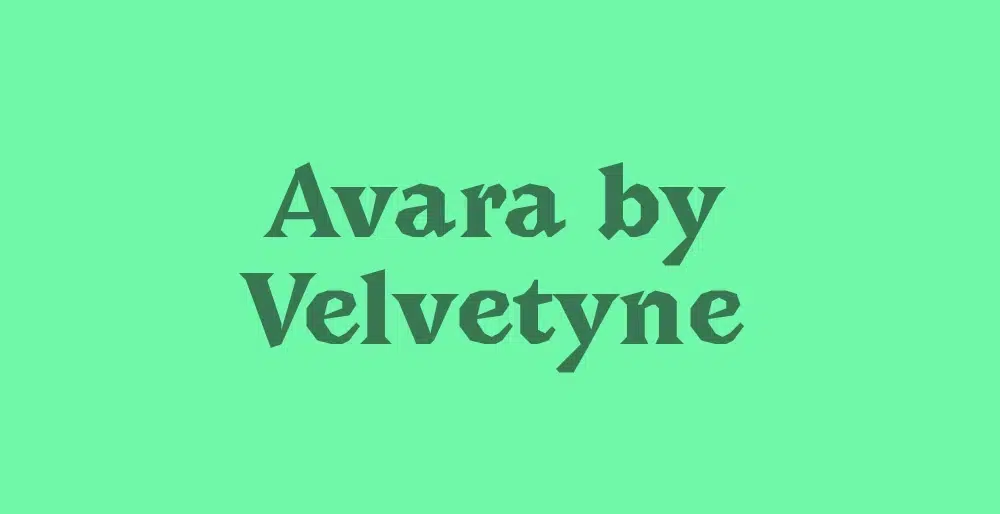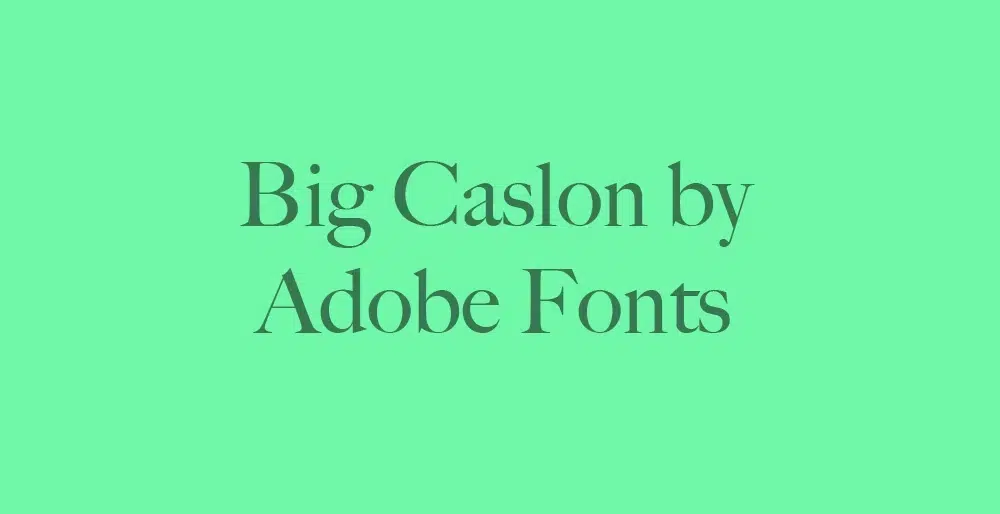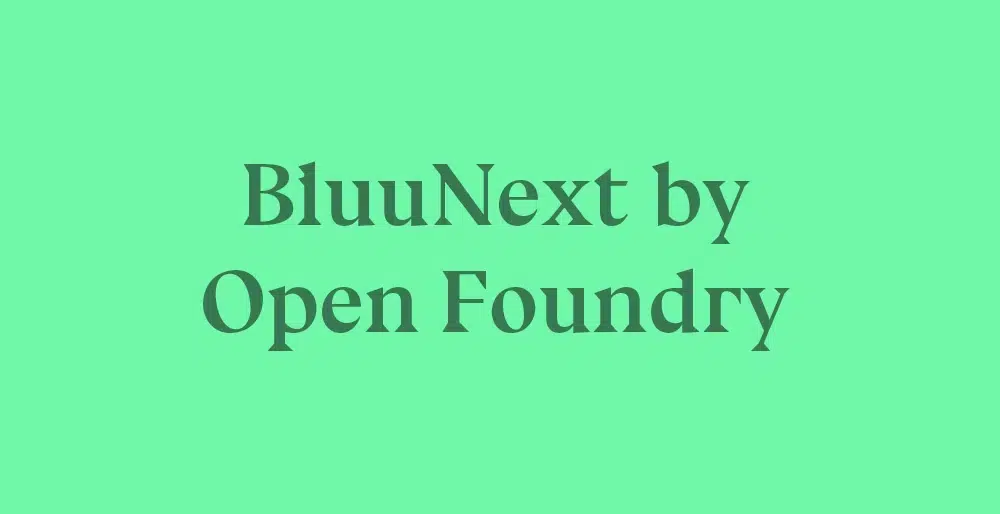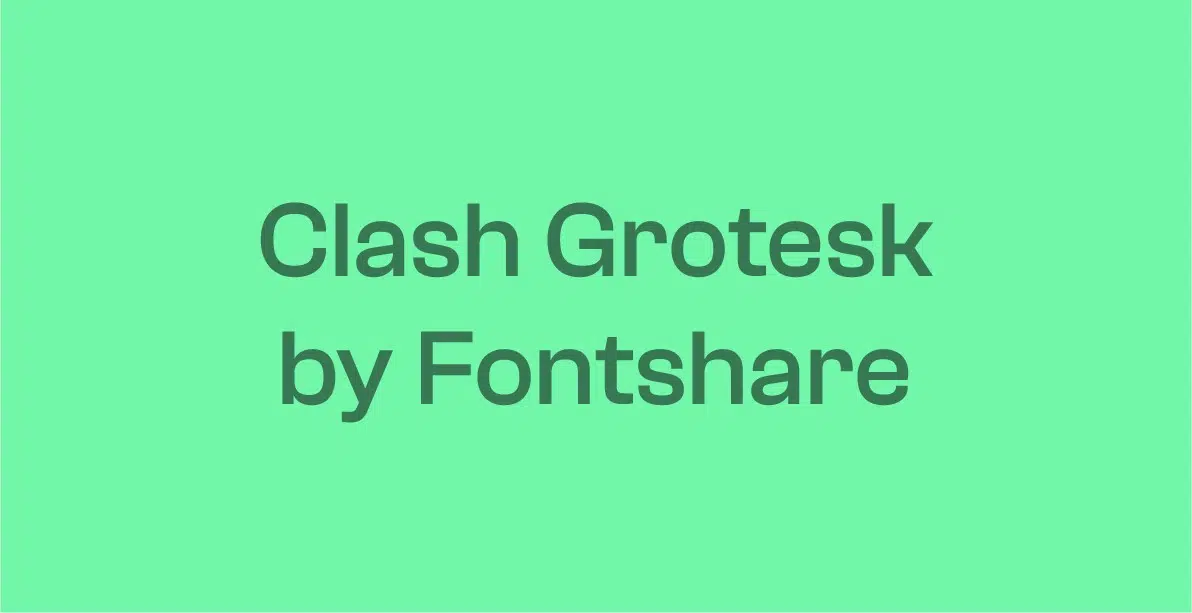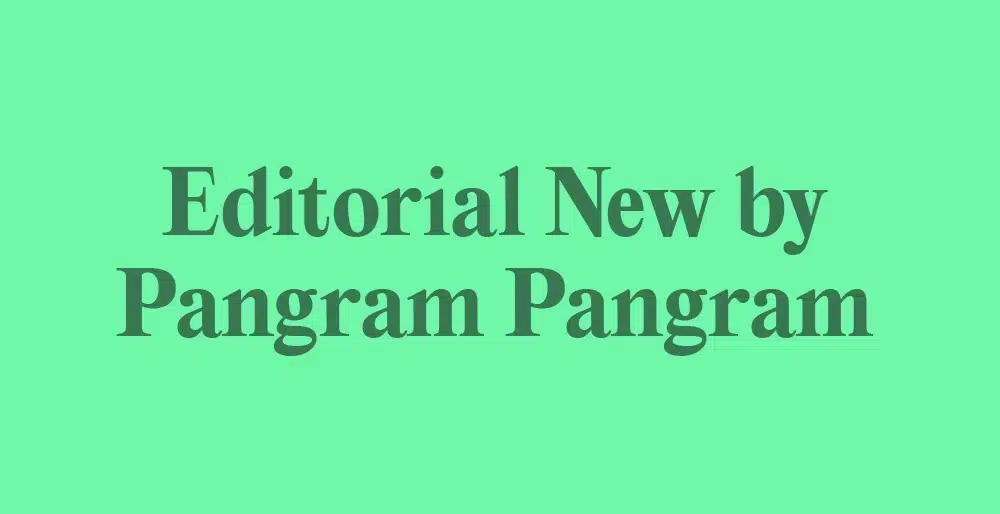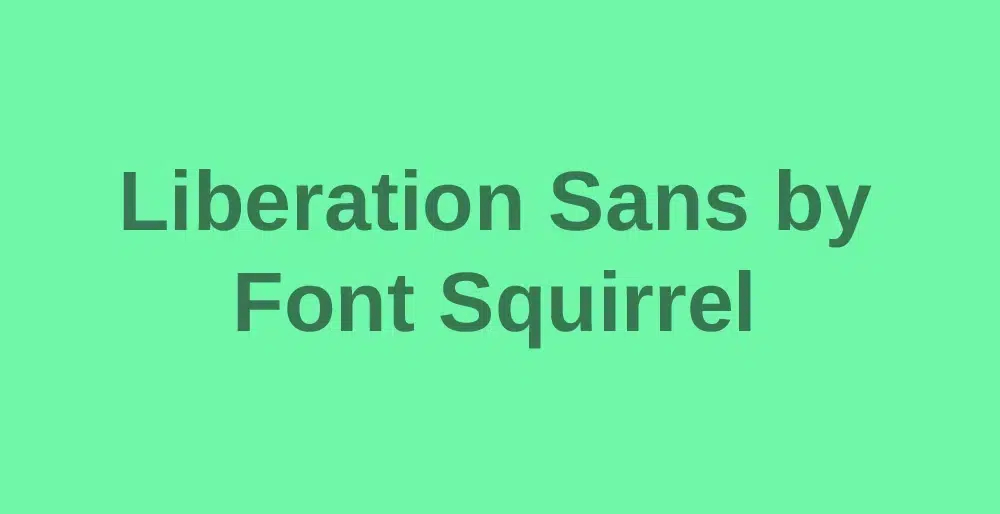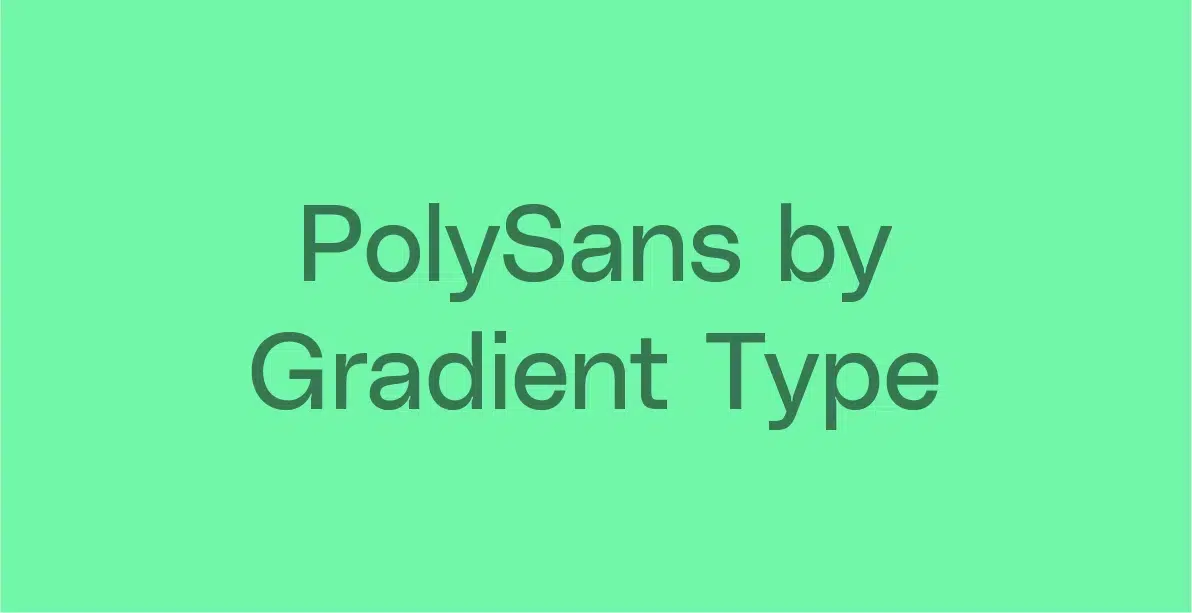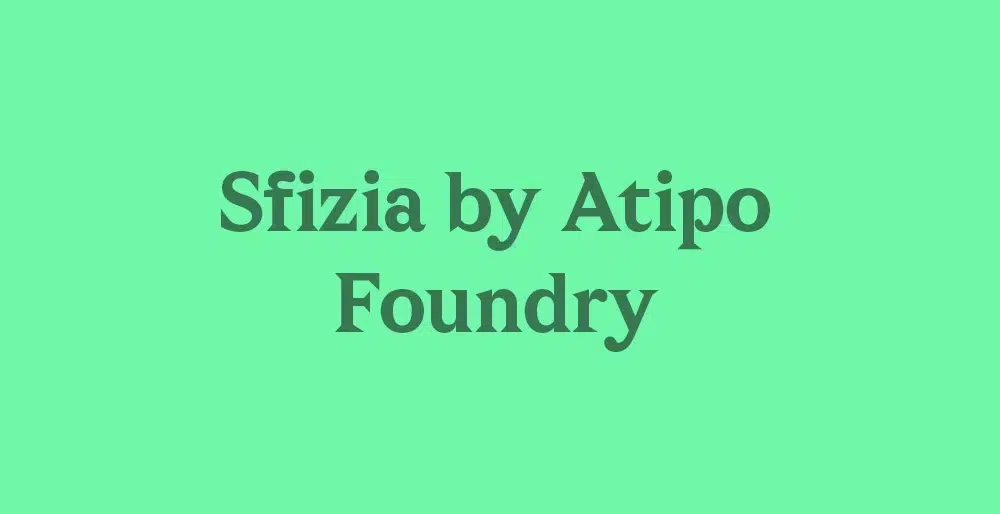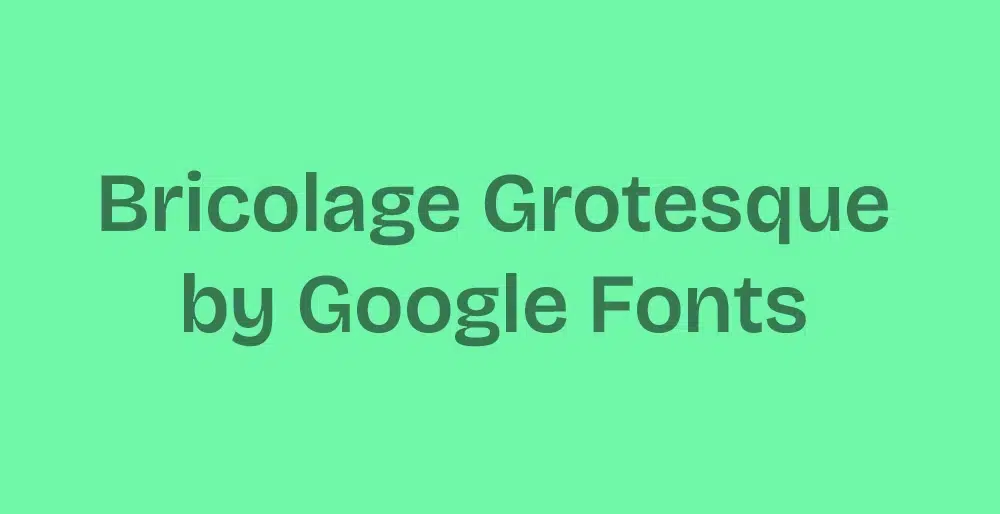
Ich sehe das ständig bei kleinen Unternehmen. Die meisten entscheiden sich nicht absichtlich für die falschen Fonts, sondern nutzen einfach die Schriften, die bei ihrer Website-Vorlage dabei waren, oder die ihnen an diesem Tag in Canva gut gefallen haben. Das Problem dabei ist, dass die Marke am Ende sowohl unzusammenhängend als auch austauschbar wirkt.
Noch bevor die Leute auch nur ein einziges Wort lesen, nehmen sie unterbewusst deine Typografie wahr. Innerhalb eines Bruchteils einer Sekunde verrät deine Schriftwahl, ob dein Unternehmen traditionell, zuverlässig, innovativ oder vielleicht sogar ein wenig exzentrisch ist.
In diesem Artikel stelle ich dir die 27 besten Websites vor, um Schriftarten zu finden. Du erfährst außerdem, was du 2026 über Font-Lizenzen wissen musst und wie ich als Markendesignerin Schriften für meine Kunden auswähle. Springe einfach direkt zu dem Abschnitt, der dich interessiert, oder lies den gesamten Artikel.
- Adobe Fonts (included with Creative Cloud)
- Monotype
Die 27 besten Webseiten, um Schriftarten für deine Marke zu finden (A–Z)
Adobe Fonts ist in jedem Creative Cloud-Abo enthalten und bietet eine riesige Library, die sich perfekt zum Testen während der Designphase eignet.
Für eine bessere Website-Performance empfehle ich, die finale Schriftart direkt bei der Foundry zu kaufen und selbst zu hosten, sobald die Entscheidung gefallen ist.
Atipo bietet zeitgemäße Schriftarten mit viel Persönlichkeit. Ihr „Pay-what-you-want“-Modell ist großartig, wenn du ein knapperes Budget hast.
Die Auswahl ist zwar nicht riesig, aber wenn du etwas Markantes suchst, ohne das Budget zu sprengen, ist Atipo einen Blick wert.
Commercial Type ist eine der angesehensten Foundries der Branche und steht hinter Klassikern wie Graphik und Neue Haas Grotesk.
Zu ihren Kunden zählen Bloomberg, Vogue und die Financial Times, was Bände über ihre Qualitätsstandards spricht.
Creative Market ist ein Marktplatz für einzigartige Fonts. Weil es eine offene Plattform ist, schwankt die Qualität, du solltest also sorgfältig auswählen. Dafür ist es ein guter Ort, um Indie-Creator zu unterstützen und einen Font mit echtem Charakter zu finden.
Achte nur genau auf die Lizenzstruktur. Die Fonts sind in Desktop, E-Pub, App und Web aufgeteilt, was teuer werden kann, wenn deine Marke auf mehreren Plattformen präsent ist.
Dinamo ist ein Premium-Studio für Schweizer Typografie. Ihre Schriften haben viel Charakter und stechen aus der Masse hervor. Sie sind allerdings am besten für Marken mit einem ernsthaften Budget für Typografie geeignet.
Diese unabhängige Foundry bietet wunderschöne, moderne Schriftarten an, die man nicht überall sieht.
Ihre Fonts wurden von Marken wie Nike, YouTube und Facebook verwendet. Du kannst dort kommerzielle Lizenzen kaufen oder eine maßgeschneiderte Schrift in Auftrag geben.
FontSpace listet über 130.000 kostenlose Schriftarten auf, von denen etwa 18.000 für die kommerzielle Nutzung freigegeben sind. Es ist eine lange, unkuratierte Liste, daher brauchst du ein scharfes Auge, um etwas zu finden, das wirklich zu deiner Marke passt.
Wenn du Geduld hast, lohnt sich das Stöbern dennoch. Achte nur darauf, die Lizenz zu prüfen, bevor du etwas herunterlädst.
Font Squirrel ähnelt FontSpace mit einem großen Archiv an kostenlosen Schriftarten. Der Unterschied ist, dass Font Squirrel alle Fonts auf ihre kommerzielle Nutzbarkeit prüft, sodass du dir weniger Sorgen um die Lizenzierung machen musst.
Ihr „Font Identifier“-Tool ist ebenfalls sehr nützlich: Lade ein Bild einer Schriftart hoch, und es findet ähnliche Fonts für dich.
Fontshare ist eine meiner Lieblingsseiten, um kostenlose Schriftarten zu finden.
Sie wird von der Indian Type Foundry betrieben und bietet eine sorgfältig kuratierte Auswahl an hochwertigen Fonts wie General Sans, Clash Display und Supreme—alle in mehreren Schriftschnitten und inklusive integrierter Kombinationsvorschläge.Clash Grotesk von Fontshare — moderne Free-Font-Schriftart für das Branding
Welche Brand Fonts du auch wählst, prüfe immer die Lizenz und nuzte sie konsequent.